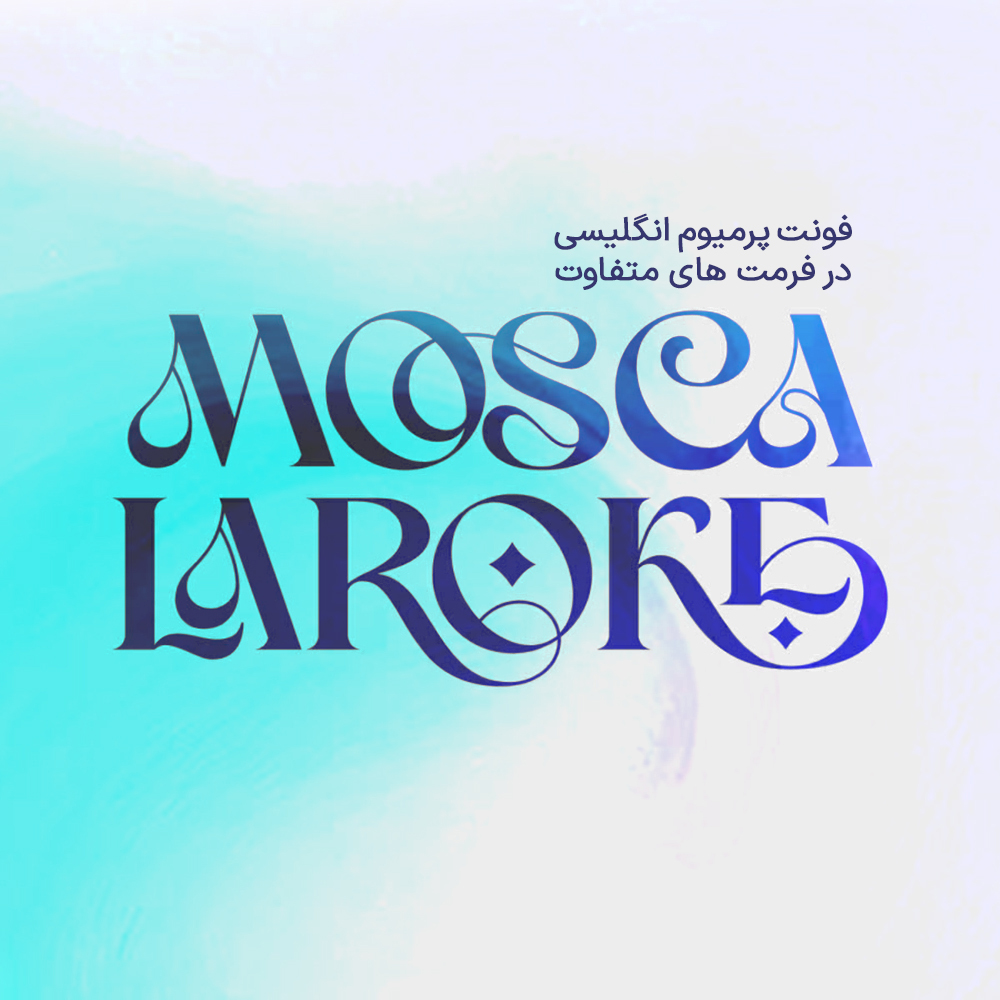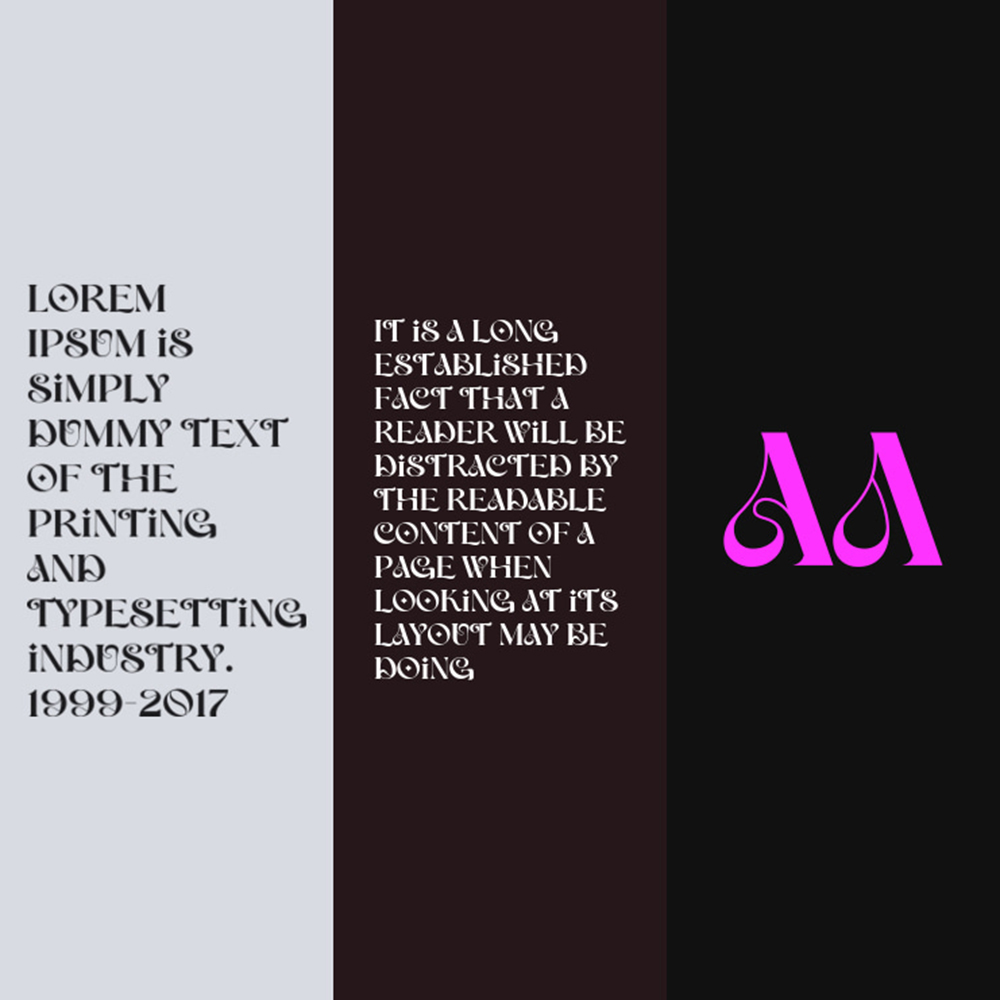
دانلود فونت انگلیسی MoscaLaroke Font
فونت پرمیوم و انگلیسی MoscaLaroke Font قلم مدرن بدون الهام از حروف مدرن با جزئیات هندسی و عمیق در اصول طراحی است. فونت MoscaLaroke یک انتخاب عالی برای هر تلاش خلاقانه، شیک، طراحی سبک زندگی مانند لوگو، تبلیغات، واترمارک روی عکاسی، لوازم التحریر، پروژه برندسازی، نمایش و مجله، دعوت نامه، برند شرکتی، طراحی محصول، برچسب، پروژه تجاری و بسیاری از پروژه های دیگر با لمس ظریف است.